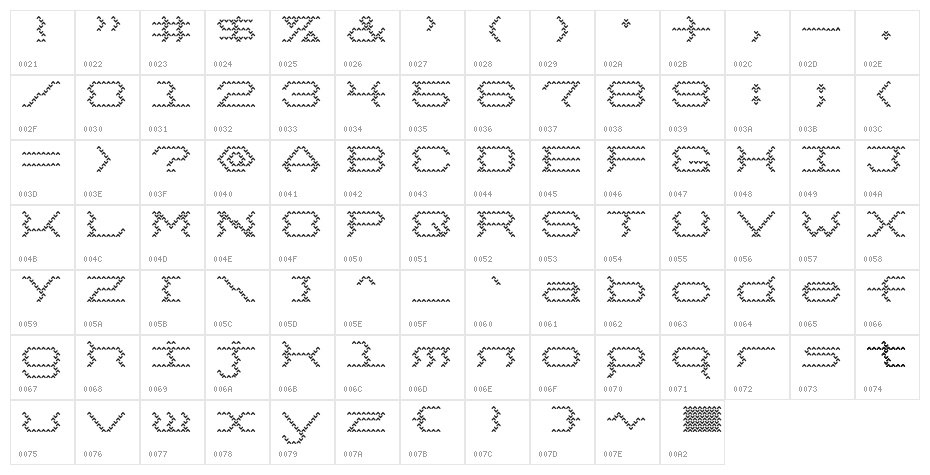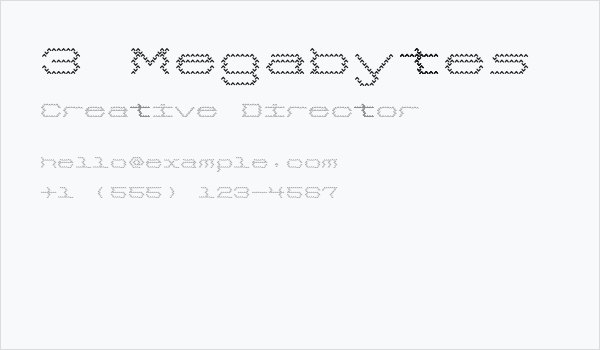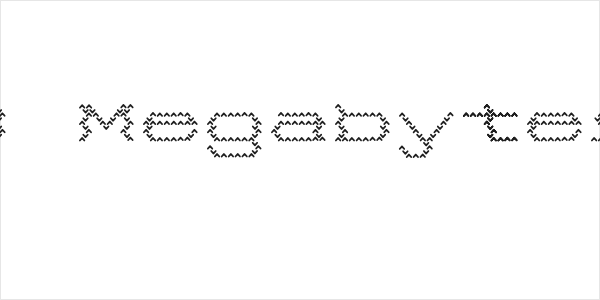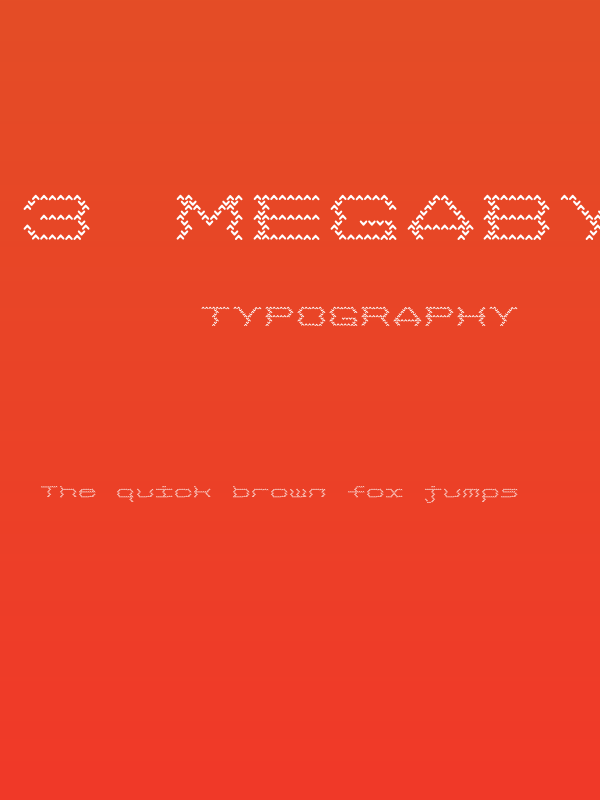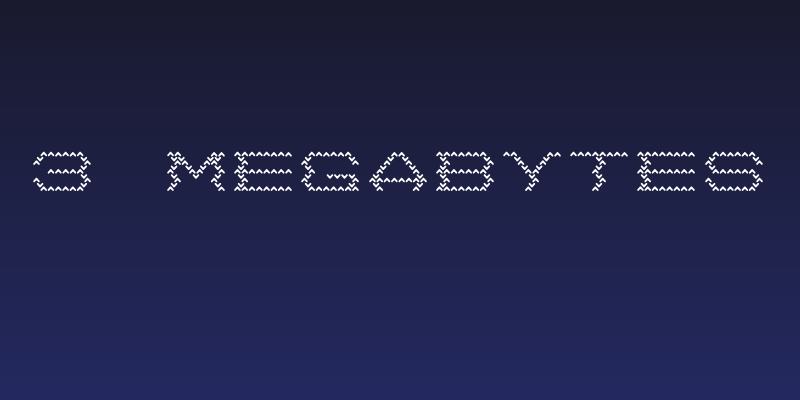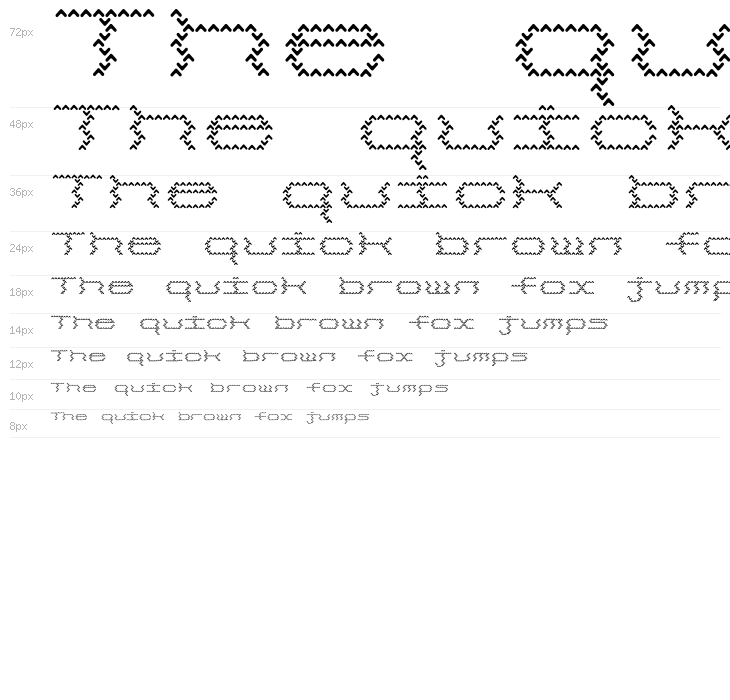
3 Megabytes Font
✎ Dotted
| Kategorien | Dotted |
| Anwendungsfall | Logos, Posters, Creative Titles |
| Vorgeschlagene Projekte | Ideal for craft-themed projects, playful branding, children's books, or any design requiring a textured, handmade feel. |